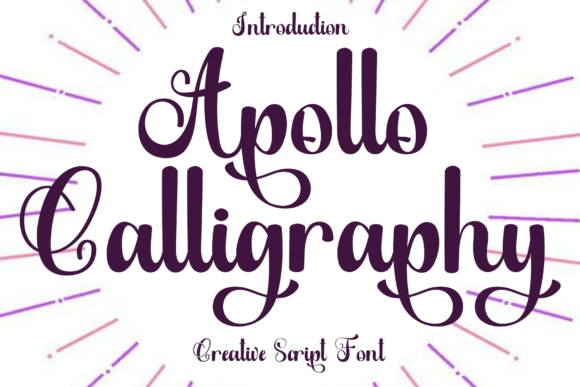
Apollo Calligraphy
Apollo Calligraphy – La police qui mêle convivialité et créativité
Vous cherchez une police qui respire la chaleur humaine tout en restant professionnelle ? Apollo Calligraphy est la réponse idéale. Ce type de caractère casual et créatif se distingue par ses traits ronds et ludiques, donnant à chaque texte une impression détendue et accueillante. Que vous travailliez sur des projets personnels, des invitations élégantes ou des visuels pour les réseaux sociaux, Apollo Calligraphy ajoute une touche hand‑drawn unique qui capte immédiatement l’attention.
Pourquoi choisir Apollo Calligraphy ?
- Esthétique chaleureuse : ses courbes douces créent une atmosphère conviviale et proche du lecteur.
- Polyvalence créative : parfaite pour les cartes d’invitation, les flyers, les posts Instagram et même les titres de blogs.
- Facilité d’utilisation : aucune courbe d’apprentissage compliquée – il suffit de sélectionner la police et de laisser libre cours à votre imagination.
- Originalité assurée : son look « fait main » se démarque des polices génériques, offrant un caractère distinctif à chaque projet.
Points forts et limites
Points forts : convivialité, lisibilité même en petite taille, large support logiciel, style unique qui reste professionnel.
Limites : peut ne pas convenir à des projets très formels ou institutionnels où une police plus « sérieuse » est requise.
Conclusion
En résumé, Apollo Calligraphy est la police idéale pour tous ceux qui souhaitent apporter une note chaleureuse et originale à leurs projets graphiques. Sa compatibilité avec les principaux outils de création et son style ludique en font un incontournable pour les designers, les marketeurs et les amateurs de typographie. N’attendez plus : téléchargez Apollo Calligraphy et laissez parler votre créativité !